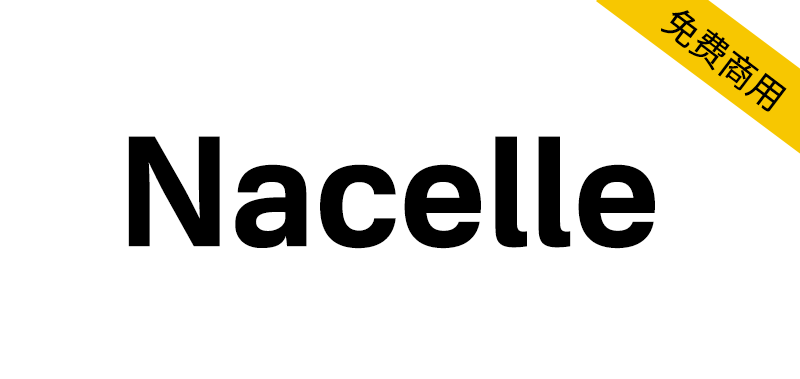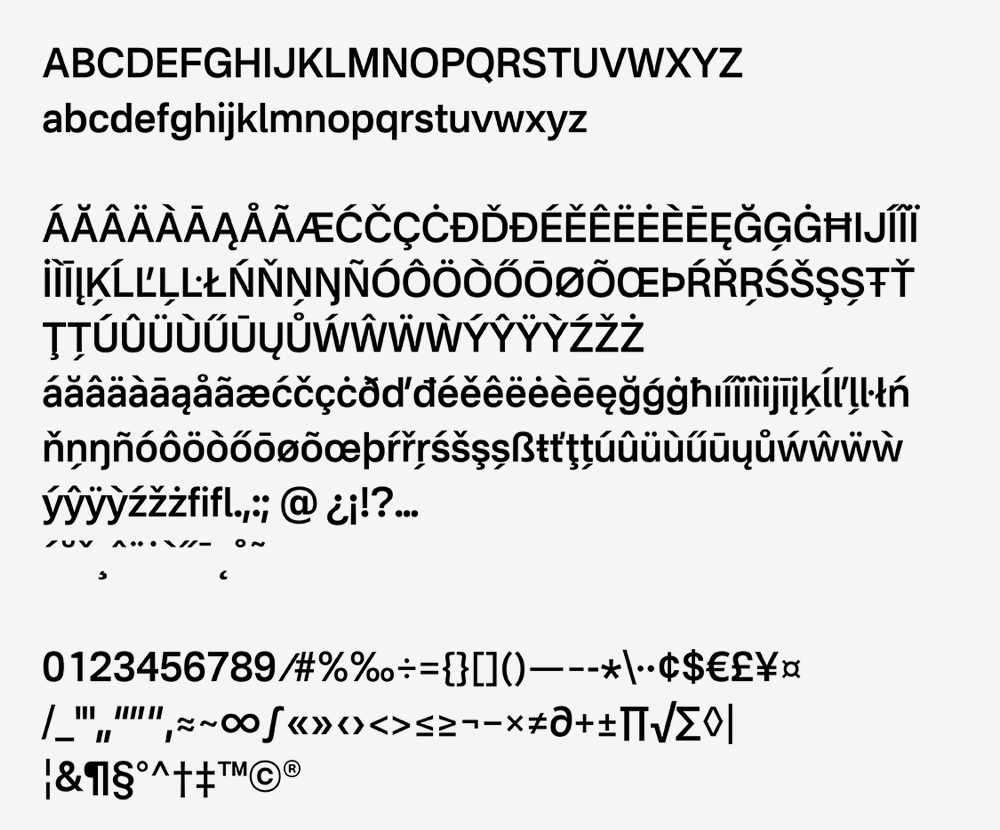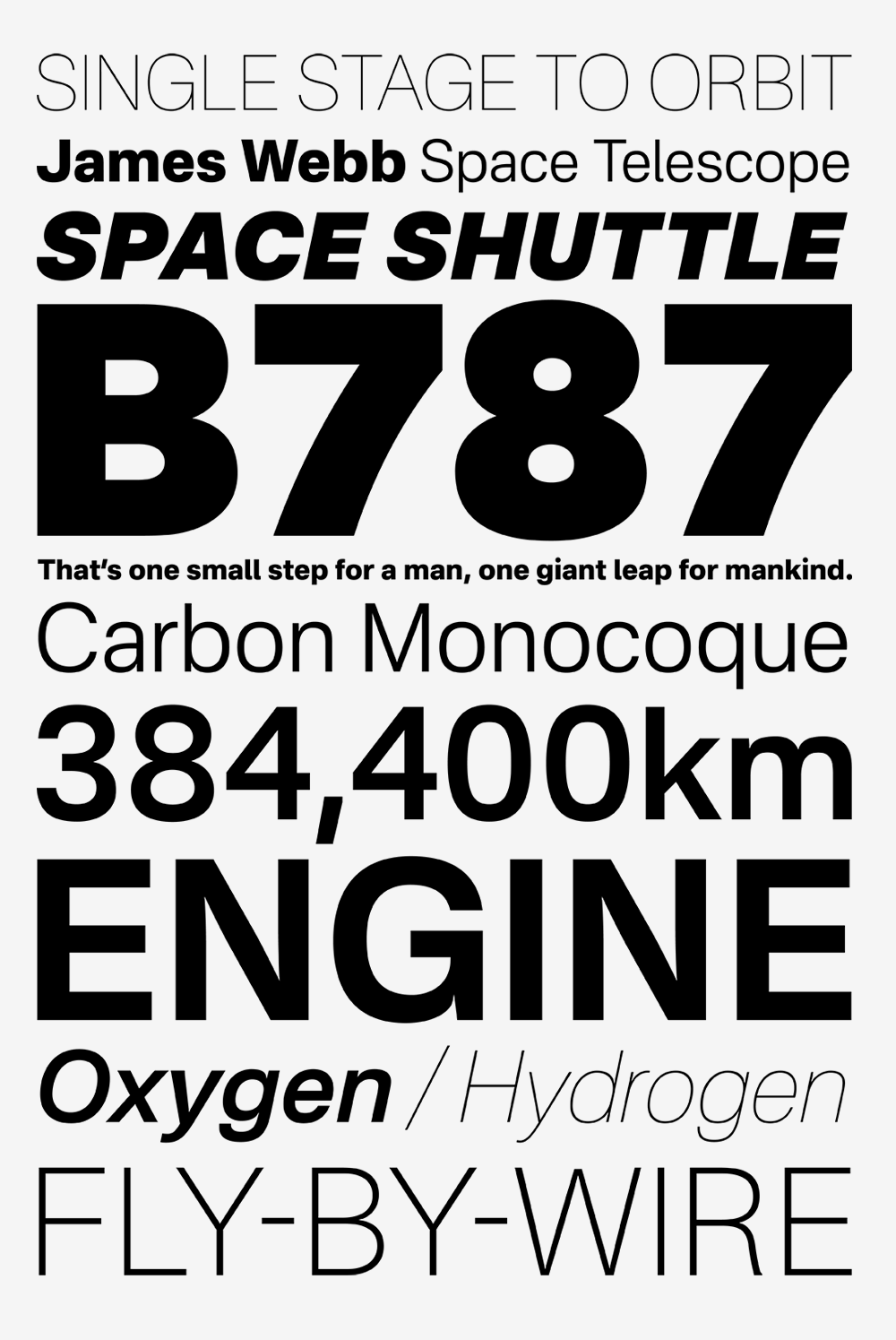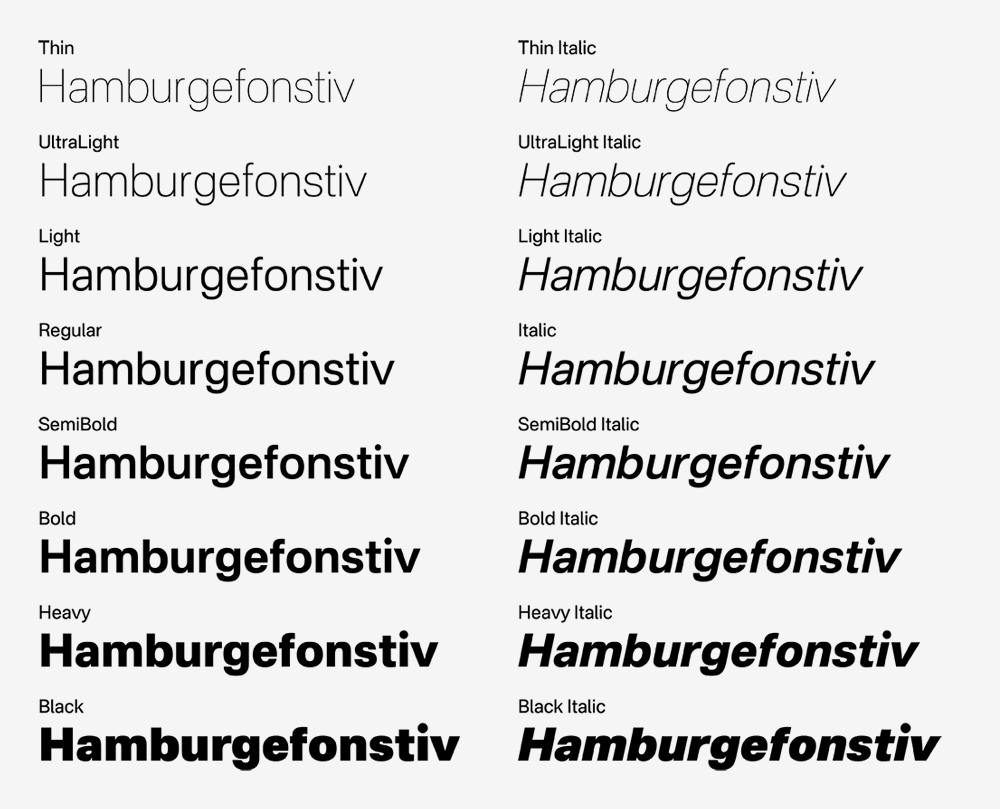
Nacelle 是一种新怪诞的无衬线字体,是在 Aileron 的基础上重新设计和彻底翻新的。在保留 Aileron 的基本概念“创建一个在用户界面上易于看到和识别的新怪诞”的同时,我们调整了指标和细节以创建更自然的形状。
NacelleはAileronのデザインを見直し、全体的に改修を施したネオグロテスク・サンセリフです。Aileronの「UI上で見やすい・識別しやすいネオグロテスクを作る」という基本コンセプトはそのままに、メトリクスや細部を調整し、より自然な形に仕上げました。